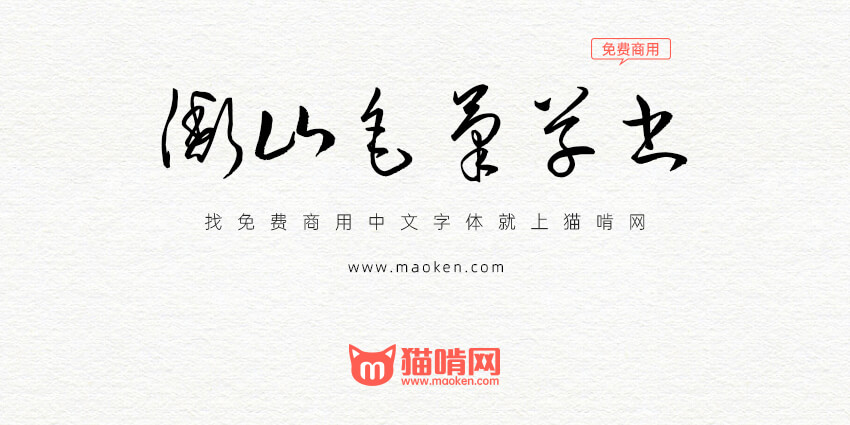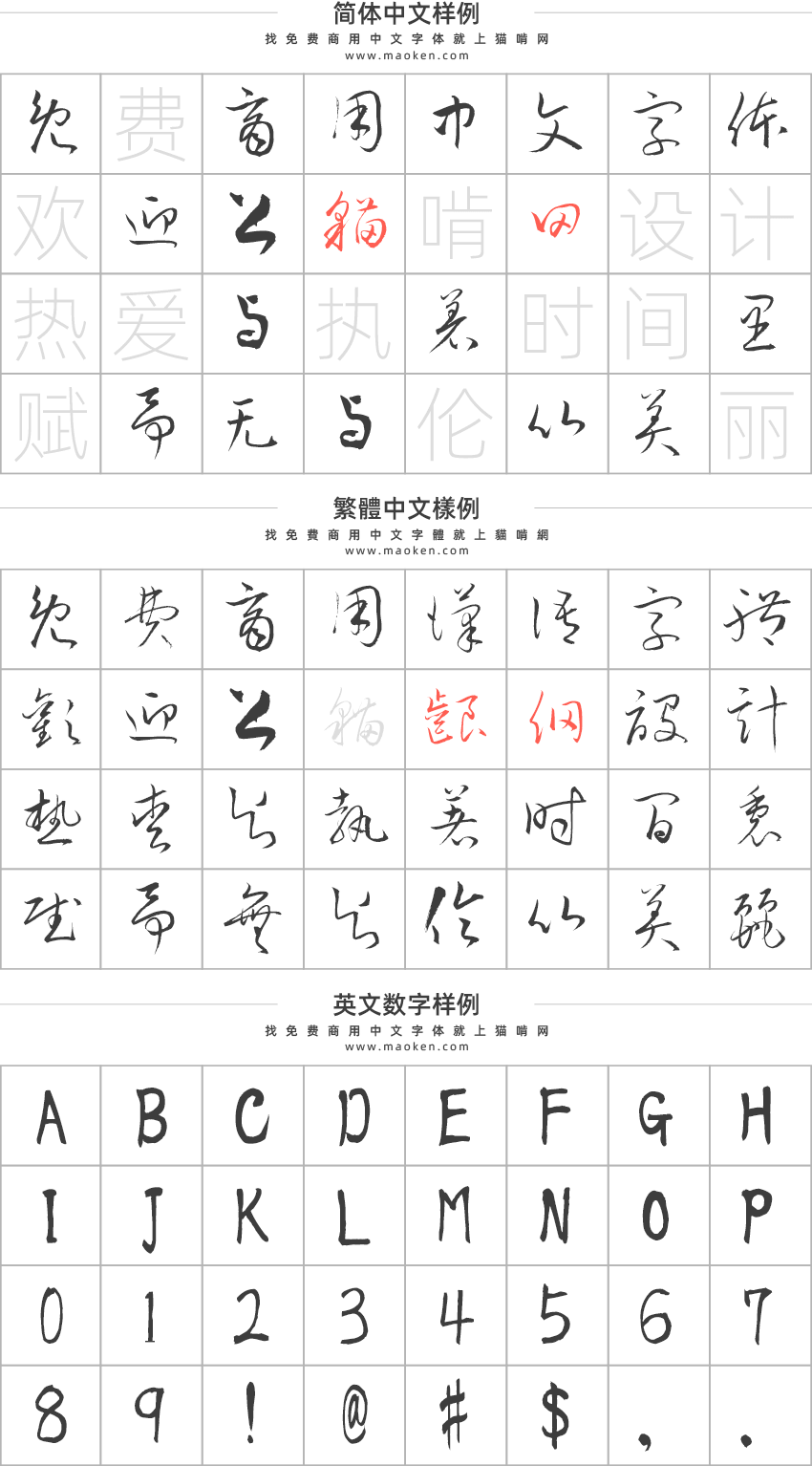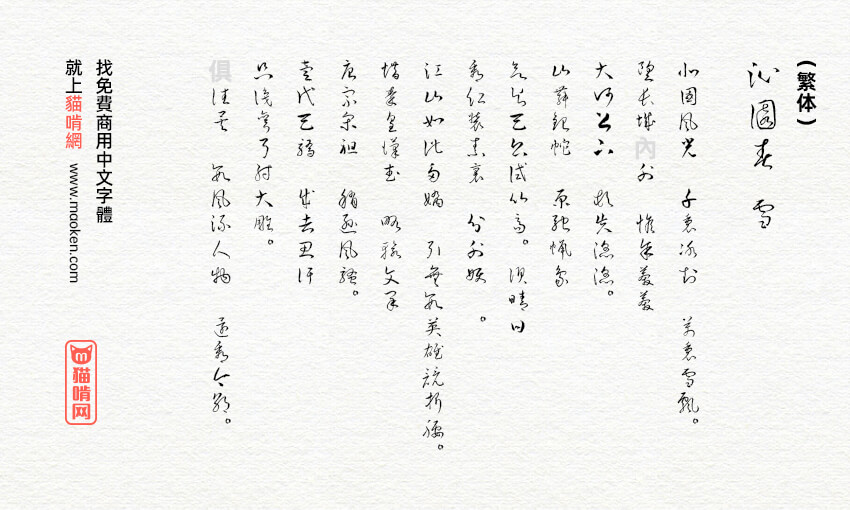
衡山毛笔草书:神闲张狂流纵横洒脱的狂草字体
字体作者:青柳衡山 (其他语种) 字体字重:1个
字体名称: 衡山毛笔草书(日文名: 衡山毛筆フォント草書 ) PS中字体名称: 衡山毛筆フォント草書 Regular
字体版本:Version 1.20 收录汉字:简体★★ / 繁体★★★★★
草书的特点是流跌宕落笔,运转龙蛇;流悬腕中锋,挥洒舞墨;流九霄拔势,神闲张狂;流纵横洒脱,一气呵成;
衡山毛笔草书是日本书法家青柳衡山先生挥毫写成的毛笔字体,这款字体行笔潇洒飘逸, 对历史相关的漫画和设计等非常有用,是非常帅气的字体。 这款字体包含JIS第1水准2965字,第2水准3390字。由于字体采用的日本的JIS标准,所以支持的简体字数不算多,但是繁体却是比较齐全的。